Khám phá font chữ đằng sau logo các thương hiệu nổi tiếng
Điều gì sẽ xảy ra nếu bạn tác font chữ ra khỏi một thiết kế logo nổi tiếng ? Đôi khi sự khác biệt diễn ra không nhiều lắm.
Facebook có logo sử dụng font Klavika. Bạn có thể tìm ra điểm khác biệt giữa phiên bản chữ trong logo và chữ của font gốc? Hai phần của chữ k đã được khép sát lại với nhau và chữ c cũng được làm rộng hơn một chút.
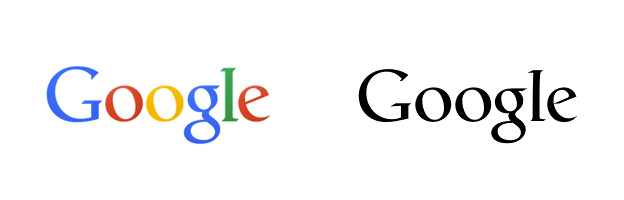
Logo của Google dựa trên font chữ Catull BQ. Sự khác biệt ở đây chỉ có một chút nhỏ: thanh ngang ở chữ e mỏng dần ở phía cuối so với logo phiên bản màu sắc. Việc dùng màu sắc chính là chìa khóa làm nên đặc điểm nhận dạng của logo Google.
Vimeo
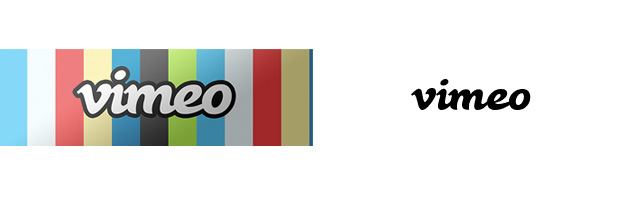
Logo của Vimeo cơ bản dùng font chữ gọi là Black Rose. Vè cơ bản các chữ cái đã được đặt sát nhau hơn, kết dính chữ v và chữ i và có ít khoảng trống giữa chữ m, chữ e và chữ o hơn.
PayPal
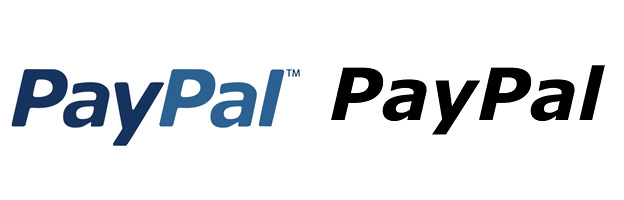
Không còn hoài nghi gì về sự xuất hiện của font Verdana ở đây. Font chữ này đã được sử dụng cho logo Paypal tuy nhiên họ đã gọt các đầu nhọn của chữ cái khiến cho logo có một chút hơi hướng retro.
TMZ
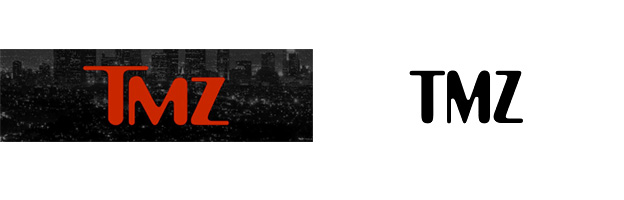
TMZ có thiết kế logo sử dụng font chữ Amelia. Chữ T đã được làm to hơn vì thế nó lấn cả sang chữ M. Các chữ cái khác cũng đã được tăng chiều rộng hơn.
Flickr
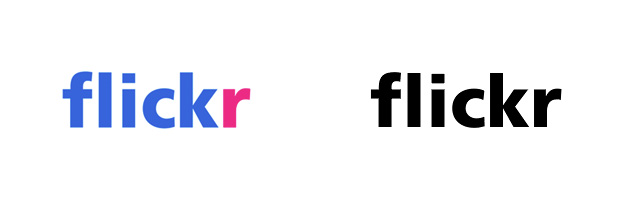
Nếu không có màu sắc thì chắc chúng ta cũng khó nhận ra sự khác biệt giữa phần chữ trong logo chính thức của flickr và riêng phần chữ khi được viết riêng. Logo của thương hiệu này sử dụng font Frutiger.
Absolut
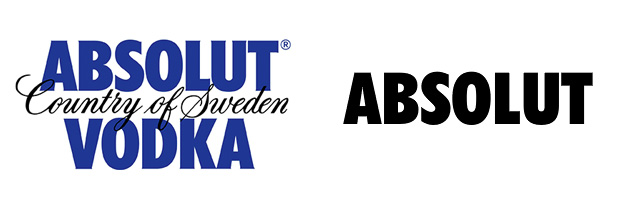
Logo của Vodka dựa trên cảm hứng của một logo rất nổi tiếng là Futura. Nếu nhìn thật kỹ,phần chữ của logo chính thức của hãng đã được thêm một chút serifs khiến cho font chữ trở nên năng động hơn.
YouTube
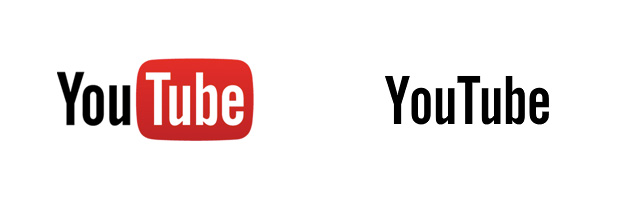
Không có sự khác biệt nhiều giữa font chữ khi nằm trong và nằm ngoài logo của Youtube . Font chữ của nó rất tuyệt vời: Al-ternate Gothic No. 2. Những từ ngữ được chia cách bởi khoảng cách hợp lý và một khối màu đỏ đã bao trọn chữ Tube trong thiết kế logo chính.
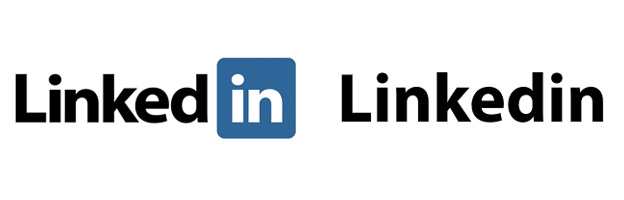
Linkedin sử dụng phiên bản đậm nét của font Myriad Pro, người ta cũng đã giãn cách chữ In và đóng khung nó vào một khối màu xanh.
Giorgio Armani
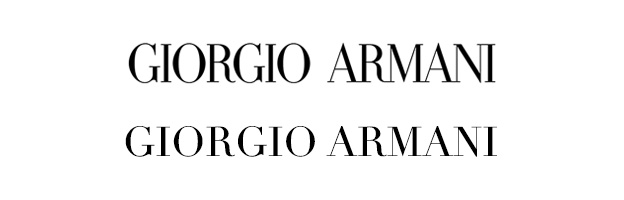
Ta có thể gọi font chữ mà logo này dùng là modern serifs. Nó có sự kết hợp giữa các nét dày và mỏng, tạo nên vẻ đẹp của thương hiệu sang trọng này.
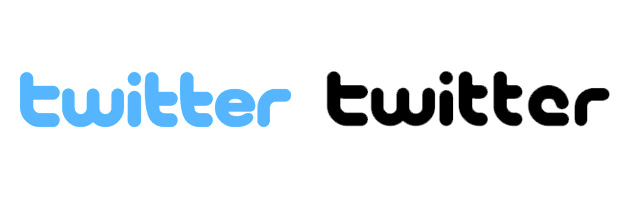
Twitter dựa trên font chữ Pico. Hai chữ T và chữ E đã được chỉnh sửa lại đôi chút so với font chữ nguyên bản.
Skype
Skype luôn sử dụng font Helvetica, có lẽ là một trong những font chữ phổ biến nhất mọi thời đại. Khi được sử dụng trong phiên bản logo chính trong hệ thống nhận diện thương hiệu, người ta đã khép chặt các điểm trên các chữ cái lại với nhau và bao quanh chúng bởi hình ảnh bong bóng.